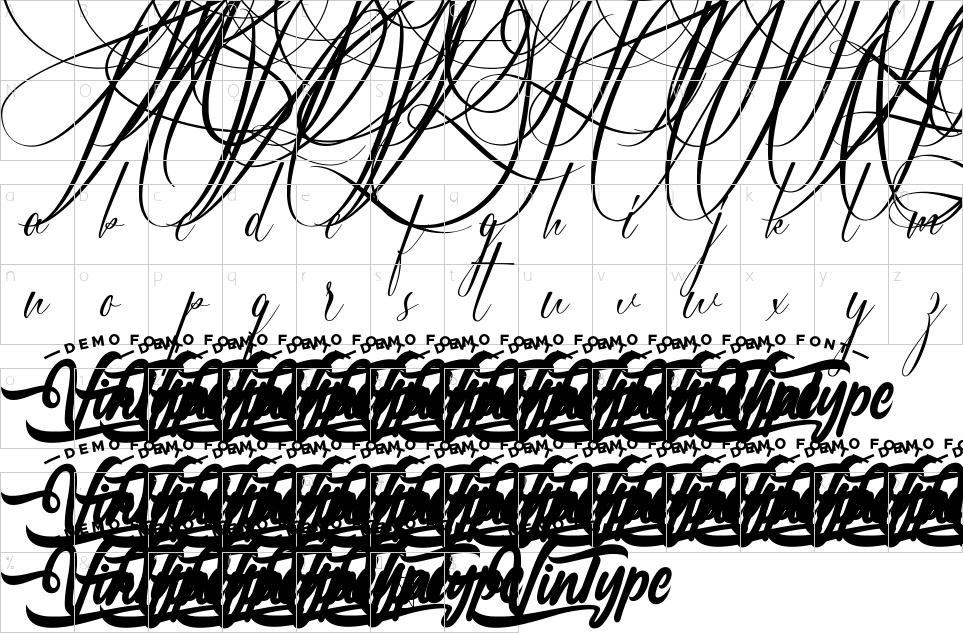
A Diamond Flower Font é uma elegante seleção para designers que buscam adicionar um toque singular às suas criações digitais. Desenhada por vintype, esta fonte proporciona uma experiência única em dispositivos Windows e Mac. Com seu design detalhado e sofisticado, a Diamond Flower oferece caracteres precisos e fluidos, permitindo que os designers criem textos de alta qualidade com um ar inconfundível. Esta fonte foi baixada 2687 vezes por designers ansiosos por novas maneiras de expressar suas ideias gráficas. A Diamond Flower é a escolha perfeita para quem procura uma fonte clássica e moderna, que adicionará um toque distintivo às suas criações digitais. Em sua versão gratuita, ela traz um pouco do encanto da arte floral à sua composição digital, sem comprometer o desempenho ou a estética.